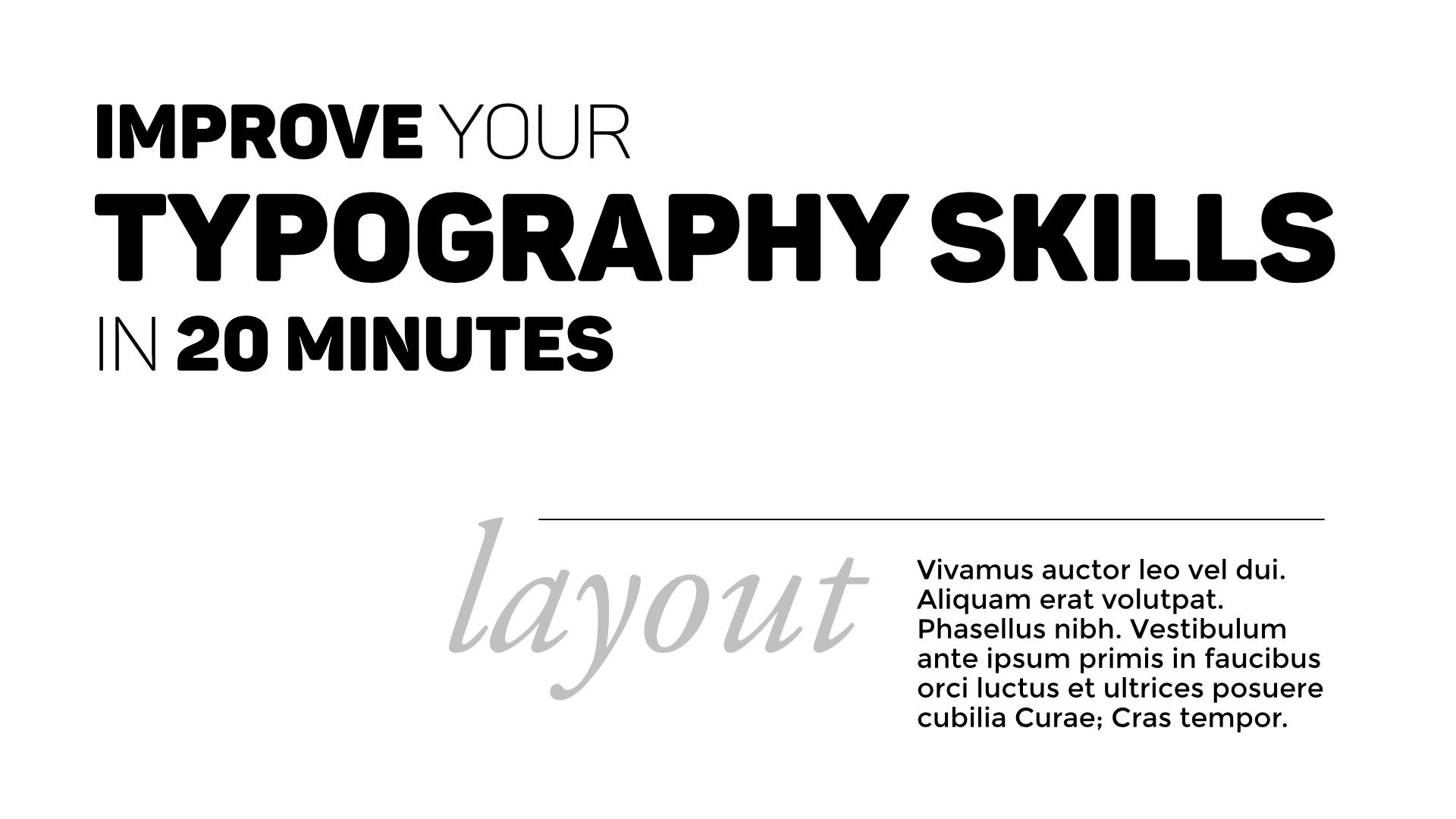
Améliorez vos compétences en typographie en 20 minutes
Introduction
Aperçu, mouvement des yeux et texte du corps
Principes de base. Mise en page, arrangement, répétition et contraste
Plus et plus de texte
Conclusion et devoirs
À propos de ce cours
Dans ce cours court, je vais partager quelques principes sur le type et le texte qui vous aideront à créer un meilleur format avec du texte plus lisible.
01 Aperçu général. Mouvement des yeux, du leader, de l'espacement, du texte du corps.
02 Principes de base
02.1 Mise en page
02.2 Arrangement
02.3 Répéter
02.4 Contraste. Des façons de créer un contraste.
• Mélanger des polices de caractères
• Taille
• Poids
• Direction
• COULEUR
• Les images
Mélanger des polices de caractères. Comment créer de l'harmonie et du contraste au lieu de conflit en utilisant le type.
La classification des polices simplifiée.
03 De plus en plus de textes
• Indents
• Listes et onglets
• Accidents
• Flou
• La règle de trois lignes
• L'effet spot
• L'optique du kerning
• Améliorations
• Colonnes
• Orphelines
• Laisser tomber des bouchons
• Marge optique
• Tous les bouchons
• Les grilles
04 Conclusion et devoirs
1. Introduction: Bonjour et bienvenue. Je m'appelle Victor. Vegan Diamond Libertés en graphiste. Dans cette classe, je vais partager quelques principes sur le type et le texte qui vous aideront à créer une meilleure mise en page avec du texte plus sympathique. Si vous avez des problèmes avec des documents simples qui contiennent des taxes, s'il vous plaît prendre un café et rester avec moi pendant 50 minutes. À la fin de ces courts cours, je vous promets que vous aurez une meilleure compréhension de travailler avec la copie, arrangement de mise en page et bien plus encore. Cette classe créée principalement pour les débutants, mais j'espère que tout le monde y trouvera quelque chose d'intéressant. 2. Aperçu du texte, mouvement des yeux et du texte du corps: saleté hors typographie est sur l'esthétique et la capacité des jambes. Le but, si elle est de créer un contenu qui attire l'attention et est facilement compréhensible, et c'est tout. Pour comprendre comment cela fonctionne, nous devons examiner comment notre cerveau traite l'information au lieu de lire des caractères. cerveau d'une personne moyenne res mots en une fraction de seconde, et l'œil saute d'une naissance à l'autre, juste à la recherche de la phrase. C' est logique. Si vous venez de faire sauter le paragraphe et remplacer le texte que nous avons trompé et était, vous verrez ce que je veux dire. Ce sont donc les livres de contenu, qui doivent être traités par votre cerveau si vous diminuez ou augmentez le gain de l'espacement principal à une valeur aussi grande ou trop petite. Je dois faire des mouvements inhabituels, et l'information sera plus difficile à traiter. Même chose va à la taille amusante quatre paragraphes. Les paragraphes avec deux grands téléphones seront plus difficiles à lire car vous êtes habitué à un mode de traitement de l' information. Une taille moyenne de la copie corporelle est généralement entre huit et 11 points, en fonction de la taille de la mise en page, Mais c'est très différent en cas de cartes de visite ou de gros tirages. Les cartes de visite peuvent fonctionner avec six ou huit points. Par exemple, si vous ne savez pas exactement ce que vous faites, suffit de laisser votre espacement tourner ou diriger Alors qu'il était dans les paramètres par défaut, Ces valeurs ont été calculées pour un résultat sympathique par des professionnels. Pour un texte plus aéré juste augmenté le début avec un ou deux points et voir si vous aimez, diminuer le début et vous verrez où vous vous retrouvez avec un paragraphe de squash, pratiquer le virage et l'espacement des lettres d'une manière similaire. Au début, nous n'aurons qu'une grande quantité de contenu avec le corps du texte. On devrait aller bien pour un livre, mais ça ne va pas marcher sur un seul biper ou une publicité. Lorsque vous devez attirer l'attention, vous devez casser le genou du moniteur en utilisant quelques principes simples. 3. Principes de base. Mise en page, arrangement, répétition et contraste: les principes de base, mise en page et la proportion du texte ING qui a une connexion logique en termes hors contenu doivent être organisés en groupes. Si vous placez plusieurs éléments proches les uns des autres, David travaille comme une unité logique. En créant de telles unités, vous aurez un contenu clair et structuré. Créer un ordre en termes d'en-têtes. Paragraphes minimaux. Capture d'images. Pensez de haut à gauche en bas à droite sur la page. Utilisez ce principe pour les adresses, les titres, les descriptions, par exemple. Au lieu de cela, essayez de faire quelque chose comme cet arrangement. Je suggère d'exposer votre copie intentionnellement. Chaque élément de votre page doit être connecté à un autre élément. En utilisant ce principe, nous allons créer une belle composition. copie peut être alignée à gauche, au centre et à droite. Elle peut être soit justifiée et pleinement justifiée. Maintenant, vous pouvez penser que le texte central attire l'attention le plus s reçu sur une affiche de film , par exemple. Mais si vous consultez quelques types de travail de référence, vous verrez qu'ils ne sont pas d'accord avec cela en raison du mouvement de la Je donne A comme il traite l'information, est préférable d'utiliser le texte en ligne gauche Maintenant pourquoi est-ce que c'est parce que vous êtes je vais trouver mieux. S' il n'a pas besoin de regarder où commence la prochaine ligne, il saura où trouver le début. Sur la ligne suivante. Vérifions un centre Tyto. Voyez-vous ces zones ? Si nous pensons à cette pièce de copie comme une image, ces zones ont été créées cheval dans l'ensemble de l'ajustement local. C' est plus difficile à lire. Il en va de même pour le texte justifié. texte justifié nécessite généralement la création de pipelines, qui cassent le texte afin que vous finissiez par rechercher des connexions logiques. Comme vous le feriez en utilisant un texte central que je suggère d'utiliser left. Je suis texto aussi souvent que possible. Sous dans la marge, vous pouvez utiliser, centré ou écrire un texte de ligne pour les en-têtes ou le texte justifié. Essayez d'utiliser gauche. Je suis le premier. Gardez à l'esprit que les gens qui investissent la culture lisent de gauche à droite, donc le texte aligné à droite et Isis pourrait être inattendu. n'y a donc rien d'autre que le texte centré et justifié. Non, ce n'est pas vrai. Le texte central peut bien fonctionner comme Heather ou le contenu sur les pagers de bombe, et justifier le texte est idéal pour les livres et les magazines. Mais en termes de capacité hors jambe, ils sont juste un pas derrière les autres, conseille un autre. À moins que vous ne souhaitiez créer une mise en page inhabituelle, essayez de garder tout à l'intérieur de vos marges. Répétez. Si vous configurez une hiérarchie, ou si vous avez utilisé quelques améliorations ou éléments graphiques, essayez de les répéter dans votre conception. Ne pas inventer un nouvel élément de conception ou un nouveau fonds pour un titre avec au milieu de la copie . Quand vous en avez déjà configuré un autre. Au début, vous pouvez répéter dans des améliorations denses, formes, espace, ses poids, fonds, fonds, tailles amusantes ou éléments de mise en page. Répéter rendra le regard de la composition unifié. Contraste. La clé pour travailler avec ce principe est d'éviter d'utiliser des éléments très similaires sur la même page. Lorsque certaines unités ont une signification différente ou proposées, essayez de les rendre très différents de l'autre unité. Cela attirera l'attention le plus un moyen de sortir, créant un contraste comment nous le faisons. Tout d'abord, en utilisant les téléphones et les polices utilisent l'harmonie ou le contraste. Au lieu de créer des conflits, nous reviendrons bientôt à cette taille. Faire la taille amusante est très différente de l'autre. Essayez d'utiliser go le ratio pour calculer les tailles. Attendez, essayez d'utiliser des poids avant qui sont très différents. Fond léger et noir. Par exemple, améliorations utilisent des éléments dans les zones situées hors de vos conceptions, telles que les tons d'arrière-plan. Souligne la direction etcetera, les lignes de l'écrivain se séparent. Nous allons briser la monotonie à gauche sur le texte, mais l'utiliser à bon escient. Couleur. Si vous avez la possibilité de travailler avec la couleur, essayez d'utiliser la théorie des couleurs pour créer un contraste. Utilisé analogique ou complémentaire fermer essayer inverser. Jetez un oeil à la couleur qui devait être qui viennent utiliser des images ou des illustrations pour briser l' argent hors. La copie. Le contenu doit être connecté à l'élément graphique. Ok, et c'est le point où nous revenons aux polices et polices de caractères. Front est un terme qui a ses racines dans l'ère de la presse de lettres. Ces collections d'air hors des formes de type matière qui étaient nécessaires pour concevoir et imprimer du texte. Un gouvernement de huit points est un différent formé d'un 10 points. Grammond italique, par exemple, Attack fait face à une collection de téléphones qui ont été utilisés améliorations telles que l'Italie, noyau board, harmonie, conflits et le contraste. Harmony est lorsque vous n'avez utilisé qu'une seule police d'une page. Ok, conflit est lorsque vous utilisez deux polices de caractères similaires ou plus sur une page. Le contraste est lorsque vous combinez des polices de caractères très différentes. Maintenant, cela s'applique à la fois aux tailles de téléphone et aux classifications de cravate. Pour vous montrer comment travailler avec, nous devons en apprendre davantage sur les classifications des fonds, mais vous allez simplifier cela. Un serif est une petite ligne attachée à la fin du trait. Dans une lettre. On peut le remonter aux sculptures de lettres romaines. Il est probablement venu à l'existence pour une raison pratique. Il était plus facile de sculpter des lettres en marbre à l'aide de petits mensonges de fermeture. riffs de Sarah ont été utilisés plus tard en calligraphie, essentiellement pour la même raison. Fait amusant. Mais c'est mieux pour les textes plus longs. Saref se connecte à la ligne de base, et ils conduisent votre œil à travers une copie plus longue. Voici quelques exemples. Par exemple, Girl Montes North Styles Saref Times New Roman est un saref baroque ou transitoire. Muthoni, ou Mort sur utilise un contraste extrême entre la langue. Donc c'est un mort sur Clarin. Don Rockwell utilise des sarees épais qui sont verticalement izés, a dit que ces types hors serif a été créé pour les affiches au 19ème siècle, Donc ce sont des polices de caractères slab serif, puis nos polices de caractères, qui essaient d'émuler les inscriptions lapidaires telles comme Fritz Quadratic maintenant ces graphismes de l'air porte la prochaine dernière est sensorielle pour grotesque. Celles-ci ont été conçues au début du XXe siècle. Tout d'abord, en évitant d'utiliser les salaires, formes plus géométriques sont apparues. Ceux-ci très considérés, hors de l'ordinaire à la fin du XIXe siècle ou au début du XXe siècle et ont été décrits comme un moyen grotesque et grotesque hors de l'ordinaire. Maintenant, ce sont des téléphones grotesques standard tels que Helvetica ou Know Scott IQ. Maintenant, il ya des polices de sens carré, qui utilisent des carrés dramatiques tels que le style Euro. Il y a des polices géométriques dans lesquelles des formes géométriques ont été utilisées pour créer leurs lettres, telles que Food, Air ou Bauhaus, et ce sont des polices humanistes, qui sont basées sur la lettres. Alors pensez, par exemple, les fils d' engrenage ou le sucre de fruits. La classe suivante est les polices de caractères de script, et dans cette classe tout est écrit à la main. Donc, leur ancien script, qui utilisent des lettres conjointes. Ce sont des scripts graphiques Kala, qui imitent la calligraphie. Il y a des polices de caractères de script noir, qui rappellent le lettrage manuscrit, et il y a des polices de caractères de script décontractées, qui sont rapidement écrites ou drones au pinceau. Et il y a une autre crête, qui est décorative, et cette catégorie est énorme, et il contient d'autres formes inhabituelles de personnages imitant des nombres numériques. Deux enfants te jetant. Pensez à tout. Vous avez maintenant un aperçu des classifications téléphoniques. Revenons à l'harmonie, au conflit et au contraste une fois de plus. Ok, donc l'harmonie n'est que le lieu. Utilisez une police de caractères sur une page. Il s'agit d'un conflit lorsque vous utilisez au moins deux polices de caractères similaires dans une page. Et le contraste est quand vous combinez des faces de matrice très différentes. Si vous le grammond sur une page tombe, c'est l'Italie peut monter des versions qui serait une harmonie avant. C' est sûr. Mais il peut être très ennuyeux si vous combinez le Gurman avec une fois nouvelle botanique romaine ou une escouade ajustement rata que nous avons un résultat en conflit en raison de leurs similitudes. Donc, ils sont tous les téléphones nécessaires, voyez-vous, et il est assez ennuyeux de regarder la combinaison frontale conflictuelle. Maintenant. Le contraste sera obtenu lorsque vous mélangez un sensible avec un serif, un script avec un san serif ou un décoratif avec le Saref, mais ils doivent être significativement différents 4. plus de texte et plus de texte: de plus en plus de texte. Voici quelques idées pour rendre votre copie plus intéressante et quelques Quiroz utilisent les Indiens par tradition. Les Indiens. Vous commencez par le deuxième ou le troisième paragraphe en les utilisant ? Vous avez séparé votre programme des aperçus sur Use Indians qui occupent l'espace au moins deux pieds, lettres au moins, ou des robinets. Si vous utilisez la liste ou les touches, vous pouvez aligner le texte qui vient après la puce, ce qui la rend plus belle apparence et plus alignée. Pour les suppléments, il était Maurin bosses et Taps. Essayez de répéter les espaces entre les pointes. Conception à l'aide d'accidents. Il y a une technique qu'on appelle accident. Tu vois, ça veut dire que c'est toi, Aaron ? Certains éléments sur le stratifié en les faisant ressembler à ils ont été créés par un accident. Maintenant, c'est quelque chose qui nécessite des années pour le faire correctement, mais il s'entraînait à floue. Si vous en avez la possibilité, essayez d'ajouter un effet de flou à votre copie pour voir s'il y a des espacements inutiles. La règle sur trois lignes. Si vous avez trois lignes qui augmentent en termes de semaine d'affilée, vous devriez éviter d'ajouter 1/4 pause. La ligne suivante ou casser l'autre sous de Si vous créez un paragraphe sans cesse croissant avec vous finira avec un gros trou dans la copie. Celles-ci mettent effet maintenant. Ceci est fondamentalement similaire à la création de contraste. L' effet sport est une technique où vous placez un objet sur vos couches si différent qu'il attire l'attention tout de suite. L' effet de soutien peut être obtenu en utilisant l'image, couleur ou la ligne de texte, optique, kern ing ou la légalisation par le fort. Différents gains sont calculés pour un bon résultat, mais c'est impossible. Avec tous les caractères possibles que vous utilisez rapidement sceller nos espaces entre les lettres de données ou les lettres ne suivent pas la forme les unes des autres. Vous devez ajuster le virage manuellement pour créer un oiseau global de meilleure qualité. Utilisez des améliorations, mais pas trop. Vous pouvez appliquer en italique Boyd ou souligner quand certains mots, mais vous ne devriez que deux ou libérer ces à moins que vous travailliez sur un texte scientifique ou technique qui l'exige. Utilisez uniquement les améliorations lorsque vous avez des raisons de les utiliser par le quatrième essayer d'utiliser pas plus de trois, et cela s'applique aux téléphones à huile et aux améliorations. Sur une page Les colonnes de mai pour le corps du texte si vous avez beaucoup d'espace pour le corps du texte Custer Utilisation colonnes sur la page, cochez les orphelins Essayez d'éviter les orphelins à la fois en bas, hors des manuels et en haut. Au lieu de cela, essayez de garder ces lignes ensemble. Vous pouvez utiliser des plafonds de travail, mais essayez de ne pas utiliser plus de trois dans une page. Pensez à utiliser des capuchons de manière inhabituelle, comme utiliser un autre téléphone ou simplement déplacer sans un peu hors de votre zone de contenu. L' alignement de la marge optique dans la conception a cette petite option. Lorsque vous l'activez, il aligne les bords gauche de chaque ligne en recherchant les bords optiques des lettres . Il en résulte un paragraphe plus sympathique. Évitez d'utiliser ou de bouchons pour le corps Les casquettes de guerre ne sont pas conçues pour le corps du texte. L' œil a besoin de tous ces blocs de construction qui sont dans les lettres minuscules orteil. Identifiez-les. Utiliser des systèmes de grille. Ok, c'est le dernier de cette liste, mais c'est très important. Donc, pour créer un look cohérent pour votre couche va essayer de configurer et d'utiliser des directives spéciales appelées salutations. Donc vos lignes étaient couchées les unes avec les autres. Cela améliorera l'apparence de vos conceptions beaucoup de jeunes notes, surtout lorsque vous travaillez avec des colonnes, vous pouvez essayer de créer des salutations horizontales à 5. Conclusion et devoirs: C' était très rapide, mais c'est juste la pointe de l'iceberg. typographie est un métier qui a besoin nombreuses années d'apprentissage et de pratique, mais s. Vous voyez, il y a plusieurs façons de créer une couche intéressante à partir d'une simple copie en utilisant quelques principes clés . Et j'ai inclus ma taxe principale dans les projets de classe pour vous. Si vous avez le temps d'essayer de les améliorer en utilisant votre application préférée, utilisez les techniques que j'ai montrées et mettez-les ici. Et nous discuterons si vous avez des questions. J' espère que vous avez appris quelques choses et que l'utilisation de ces principes a été heureuse de créer un contenu plus beau. Prends soin de toi. Au revoir.